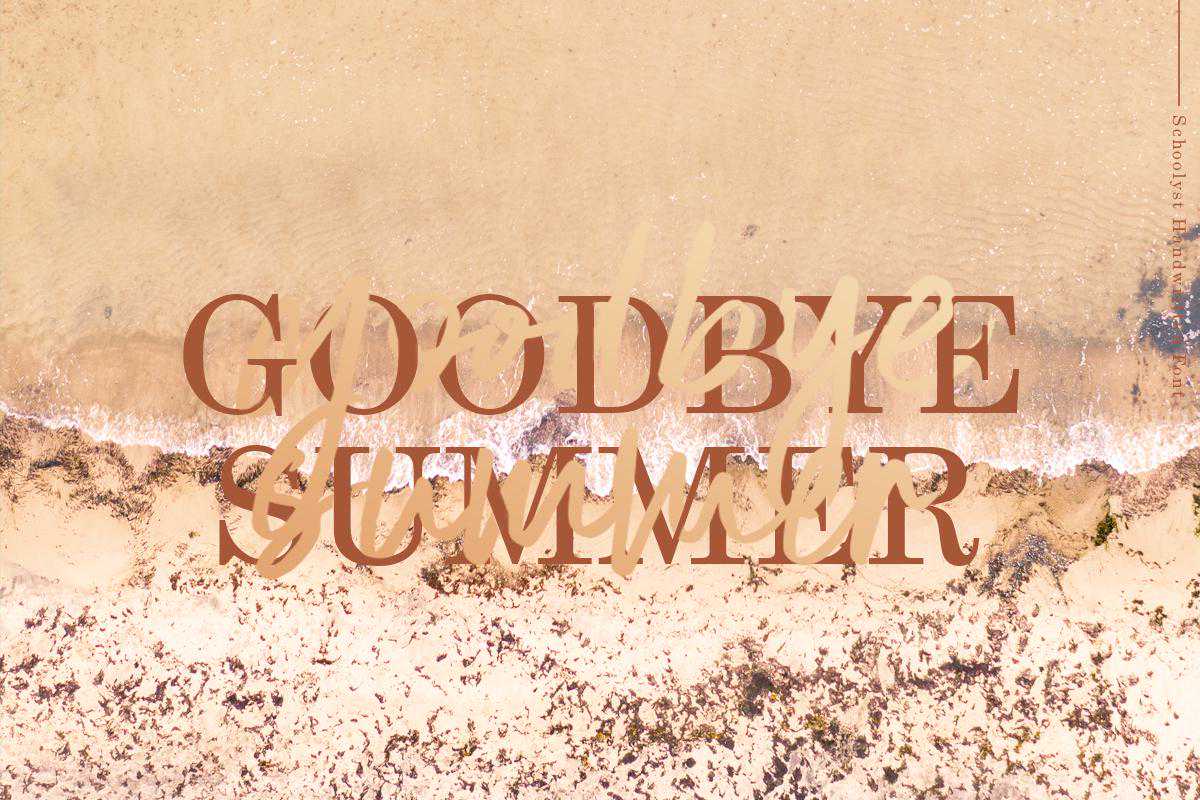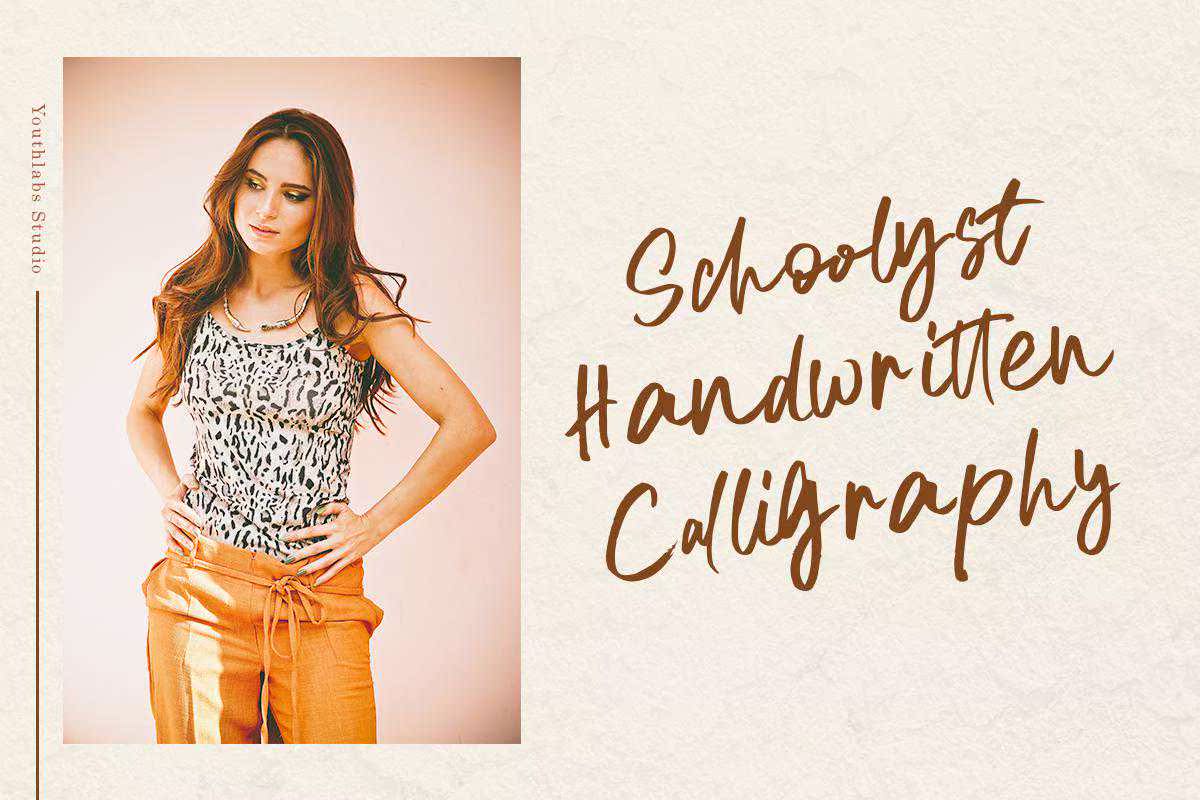
介绍SchoolystHandwitters字体。SchoolystHandwitters字体在移动到VectorMode之前使用毛刷书写和扫描。这是一种毛刷书写样式。SchoolystHandwitters有2种大写样式和3种小写样式,可以让您了解设计。介绍SchoolystHandwitters字体。SchoolystHandwitters字体使用毛刷书写和扫描移动到VectorMode.This IsourHandrittingStyle.School具有2个大写样式和3个小写样式,使您可以展开设计。